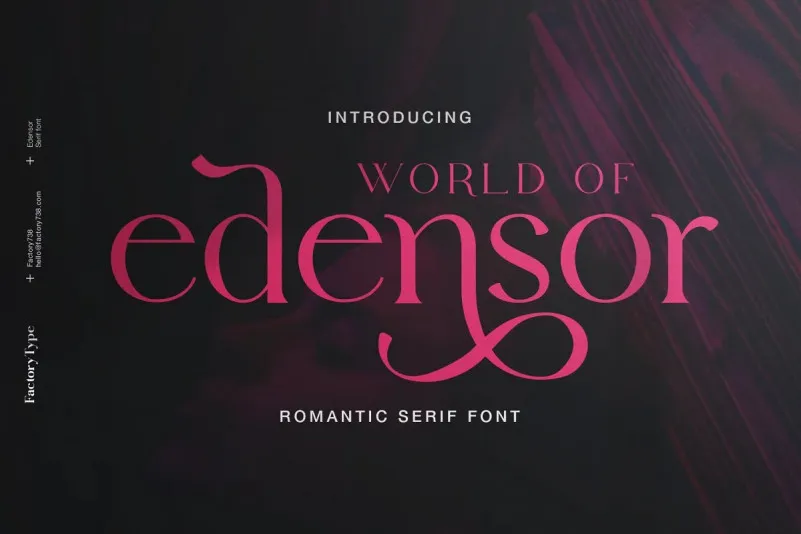
A Edensor Font é uma elegante e moderna fonte serif produzida pela Factory738. Com suas curvas suaves que atraem os olhos, ainda mantém sua comodidade classe. O conjunto de pesos variados oferece uma ampla gama de opções, permitindo que você encontre a melhor combinação tipográfica para seus projetos. As ligaturas estilizadas e alternativas disponíveis permitem que você crie um design único e criativo usando esta fonte. Ideal para qualquer projeto gráfico que exigir uma mistura sofisticada e moderna, sem perder o charme dos caracteres serif. Uma ótima opção para designers que procuram uma fonte moderna com a classe tradicional de uma fonte serif.